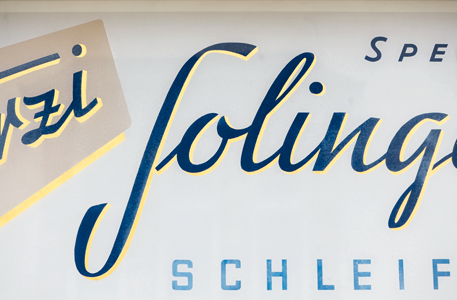
»Nicht der günstigste, aber der beste!« – So berichtet eine Ladenbesitzerin von dem in München führenden Schriftenmaler Karl Blaschke, der vor allem in den 50er- und 60er-Jahren den Fassaden der Stadt eine besondere typografische Qualität verlieh. Fast wie ein Gütesiegel fügte der prominente »Schriftkünstler« allen Arbeiten seine Signatur in kleinen, sorgfältig ausgemittelten Versalien hinzu. Karl Blaschke war – wie uns die Witwe Maria Blaschke erzählte – »ein Stück von München«.
Wer heute auf der Suche nach den übrig gebliebenen Arbeiten Blaschkes die Stadt bewandert, findet zahlreiche Beschriftungen auf höchstem typografischen und herstellerischen Niveau. Es wird höchste Zeit, sich diesem ungehobenen Schatz anzunehmen, bevor auch die letzten Beispiele langsam aus den Straßen verschwinden.